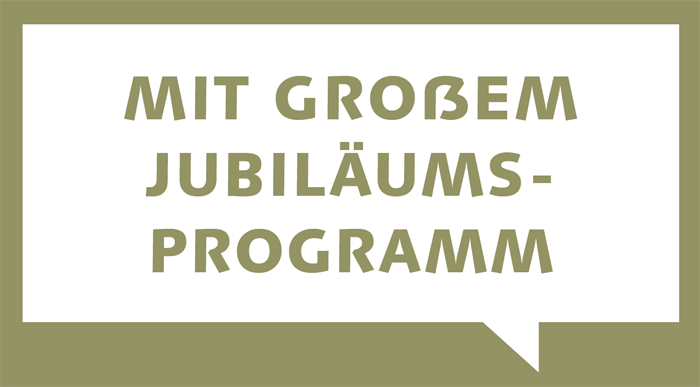
Ein Problem, auf das ich aus aktuellem Anlass gestoßen bin:
Ich sitze gerade an einer Urkunde, bei der ich vorwiegend Kapitälchen einsetze. Die Grundschrift besitzt kein Versal- bzw. Kapitälchen-ß und wird automatisch durch SS ersetzt. Nun haben sich Forssmann/De Jong dafür ausgesprochen, dass man im gesperrten Kapitälchen-Satz dieses Doppel-S auflöst und durch zwei S ersetzt, sodass die Doppel-S-Ligatur ebenfalls gesperrt wird.
Ich weiß nicht so recht, was ich davon halten soll. Ich denke, dass gerade das ungesperrte Doppel-S sinnvoll ist, um kenntlich zu machen, dass es sich ursprünglich um ein ß aus dem Minuskelsatz handelt – besonders wenn es Eigennamen betrifft.
Was haltet ihr davon? Hinkt der Vergleich, wenn man sich auf den gebrochenen Satz bezieht, bei dem Ligaturen ebenfalls nicht gesperrt wurden?
Ich sitze gerade an einer Urkunde, bei der ich vorwiegend Kapitälchen einsetze.
Ich bin kein allzu großer Freund von Kapitälchen. Sie haben für mich eigentlich nur dann einen Sinn, wenn sie als besondere Textauszeichnung verwendet werden (zum Beispiel für Verfasserangaben bei wissenschaftlichen Arbeiten). Aber für Urkunden und überhaupt sehe ich nicht recht, was Kapitälchen bezwecken sollen. Da halte ich, wenn schon denn schon, Versalien für besser geeignet. Die Kapitälchen machen ja bloß den ruhigen Eindruck, der durch die gleich großen Zeichen entsteht, wieder kaputt.
Ich denke, dass gerade das ungesperrte Doppel-S sinnvoll ist, um kenntlich zu machen, dass es sich ursprünglich um ein ß aus dem Minuskelsatz handelt – besonders wenn es Eigennamen betrifft.
Das dünkt mich nicht sinnvoll. Ich würde entweder ein normales, also gesperrtes Doppel-SS emfehlen, so wie es die Rechtschreibung auch vorsieht, oder dann aber ein ß (bzw. eben ein ?). Eine Buchstabenfolge in gesperrtem Text nicht zu sperren, wirkt wie eine selbsterfundene Regel: Unprofessionell.
Bei den im Fraktursatz nicht zu sperrenden Ligaturen ch, ck, ?t und tz verhält es sich anders: Einerseits ist das langetablierte gängige Praxis, andererseits liegen ja in den meisten Frakturschriften auch wirkliche Ligaturen vor, also Zeichen, die sich tatsächlich berühren – dies im Unterschied zum Doppel-SS.
Da halte ich, wenn schon denn schon, Versalien für besser geeignet. Die Kapitälchen machen ja bloß den ruhigen Eindruck, der durch die gleich großen Zeichen entsteht, wieder kaputt.
Entschuldige, aber das verstehe ich nicht. Ob ich alles in Versalien oder alles in Kapitälchen (ohne Anfangsversalie) setze, hat doch zunächst überhaupt keinen Einfluss auf den ruhigen Eindruck der Zeilen. Anfangsversalien im Kapitälchensatz würde ich, wenn überhaupt, nur in den von dir beschriebenen wissenschaftlichen Arbeiten o.ä. Texten verwenden. Bei den wenigen Zeilen der meisten Urkunden finde ich einen Einsatz von Kapitälchen ohne Anfangsversalien absolut vertretbar.
Einerseits ist das langetablierte gängige Praxis …
Okay, aber gibt es einen wirklich triftigen Grund dafür, außer dass es schon immer so gemacht wurde?
Eine Buchstabenfolge in gesperrtem Text nicht zu sperren, wirkt wie eine selbsterfundene Regel: Unprofessionell.
vs.
… andererseits liegen ja in den meisten Frakturschriften auch wirkliche Ligaturen vor, also Zeichen, die sich tatsächlich berühren
Fraktur-Ligaturen wie ch und ck berühren sich ja tatsächlich nicht, würde man sie hintereinander weg von Hand setzen. Aber gut, soweit ich mich erinnere, gab es diese Diskussion hier schon mehrfach.
Ich würde entweder ein normales, also gesperrtes Doppel-SS emfehlen …
So werde ich es auch handhaben. Aber mir stellt sich schon noch die Frage, was, außer der optischen Gefälligkeit, gegen das Auflösen des Doppel-S spricht. :?
Ob ich alles in Versalien oder alles in Kapitälchen (ohne Anfangsversalie) setze, hat doch zunächst überhaupt keinen Einfluss auf den ruhigen Eindruck der Zeilen.
Nur mal so aus Neugierde: warum willst du überhaupt Kapitälchen verwenden? Welchen Effekt versuchst du zu erzielen?
Ich hab’s mal getestet: bei der Linux Libertine sind die Kapitälchen in 72 Punkt praktisch identisch mit den normalen Versalien in 51 Punkt fett. Bei der Minion Pro ist’s ähnlich, nur dass da die Kapitälchen bei gleicher Höher eher den halbfetten Versalien entsprechen. (Da ich keinen halbfetten Schnitt der Minion habe, hier nur mal das Beispiel mit der Libertine.)
Es wird ja Schriften geben, bei denen die Kapitälchen ganz besondere Merkmale haben, nur stellt sich da die Frage, ob es im Sinne des Schriftgestalters wäre, sie als fettere »Quasiversalien« zu missbrauchen.
Einerseits ist das langetablierte gängige Praxis …
Okay, aber gibt es einen wirklich triftigen Grund dafür, außer dass es schon immer so gemacht wurde?
Nun, es wird ja immer behauptet, dass die Fraktur-Ligaturen nicht getrennt werden sollen, weil sonst die Lesbarkeit auf inakzeptable Weise leidet. (Nach dieser Theorie würden also z.B. in »r a c h ? ü c h t i g« die ch-Phoneme nicht mehr erkannt.) Das Problem dabei ist nur, dass man nach dieser Theorie das sch-Phonem auch nicht sperren dürfte. Da man in Fraktur »?ch« aber (teilweise) sperren soll, also z.B. »r a ? ch«, vermute ich, dass sie diese Regeln letztendlich einfach aus der Gewohnheit der Setzer eingebürgert haben. Bei »?ch« greift der Setzer eben so oder so 2x in den Setzkasten und kann im gesperrten Satz einfach ein Spatium zwischen das ? und die ch-Ligatur einfügen. Würde aber auch »ch« gesperrt werden, müsste er daran denken, die ch-Ligatur liegen zu lassen und stattdessen ein c und ein h zu nehmen. Da ist die Macht der Gewohnheit vielleicht einfach zu stark. :? Was meinen die Bleisetzer?
Bei „unechten“ Ligaturen, in denen die Buchstaben nicht verbunden sind, sieht das auch in meinen Augen nicht gut aus. Aber bei den Zwangsverbünden ist es nach meiner Theorie eben in Ordnung, weil sie buchstabenähnlich sind.
Zum Vergleich:
Optisch erträglich ist hier eigentlich nur das tz, vielleicht noch das ck — aber wenn man das ck akzeptiert, hat man auch das ch mit im Boot, und das sieht schon wieder ganz fürchterlich aus.
Es wurde halt einfach so gehandhabt, egal ob wir das nun gut oder schlecht finden.